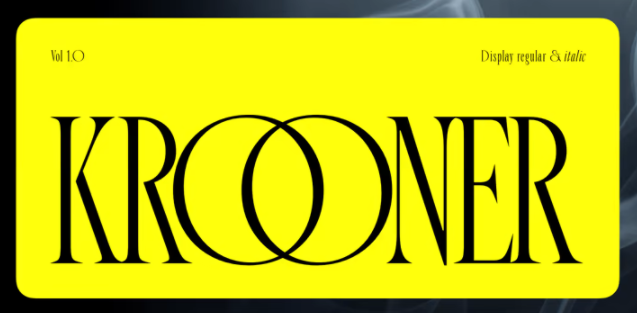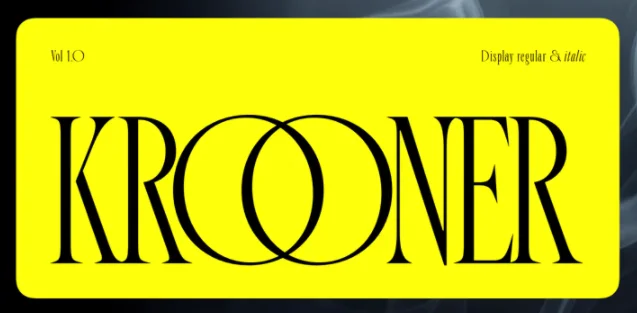
Название: Krooner Font (2021)
Krooner - это шрифт с засечками, который стремится к изысканности через элегантность. Благодаря сжатому стилю и широким круглым фигурам, он выделяется как шрифт для коротких заголовков, его курсивная версия имеет высокий уровень удобочитаемости для длинных текстов, не теряя своего стиля в небольших размерах. Символы созданы с большим уровнем детализации, что позволяет оценить их великолепие в больших размерах.
В нем более 600 знаков и лигатур, что вместе с его рациональными, гуманистическими и современными чертами засечек делает его очень универсальным для большого количества применений.